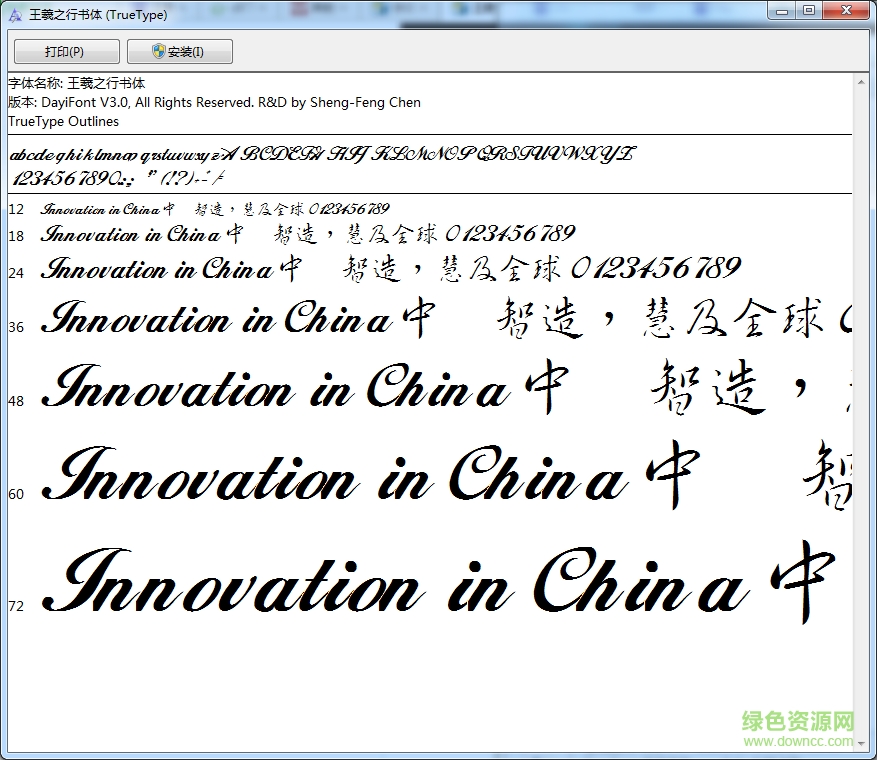
軟件介紹 軟件標簽: 王羲之行書體 字體 王羲之行書體是一款應用領域非常廣泛的書法字體,字體纖細大方,涉及多種行業(yè)使用,可直接導入ps和多種設計軟件中使用。快來綠色資源網(wǎng)下載體驗吧!王羲之行書體介紹本款王羲之字體是王羲之行書字體,下載解壓后將字體復制到C:\WINDOWS\Fonts即可。王羲之出身于一個書法世家的門庭他的伯父王翼,王導;堂兄弟王恬,王洽等都是當時的書法名手。王羲之行書字體安裝方法一:控制面板/字體/文件/安裝新字體;方法二:直接將字體復制到C:\WINDOWS\Fonts。方法三:針對win7系統(tǒng),用戶只需選中字體右鍵安裝即可。 軟件截圖 上一張下一張(1 / 1) 安裝詳細截圖 猜你喜歡 行書字體 行書字體 行書字體包括了鋼筆字行書字體大全、硬筆行書字體等,是一種介于楷書和草書之間的字體。為什么這樣說?因為行書字體既有草書的流暢感,又有楷書的端正感,可以說,行書結合了草書和楷書的特點,形成了獨特好看的行書字體。喜歡的朋友,趕快下載體驗吧! 查看更多>> 繁體行書字體 9.76M/中文/4.0/免費版下載 winman tun10011字體 17.57M/中文/6.6/下載 南構嘉飛行書字體 10.00M/中文/6.6/下載 c g流麗行書體繁/簡 4.39M/中文/5.0/下載 北方行書簡體 2.63M/中文/7.2/下載 qxyingbixing 1.26M/中文/8.0/下載 其他版本下載 標題 大小 更新日期 下載 下載地址 電腦版 王羲之行書體 點擊報錯 軟件無法下載或下載后無法使用,請點擊報錯,謝謝! 關閉報錯反饋 請描述您所遇到的錯誤,我們將盡快予以修正,謝謝! *必填項,請輸入內(nèi)容 本類最新 dreamweaver字體庫 首爾南山體字體 v1.06 官方版 潮字社風云簡ttf 潮字社凌渡鯤鵬簡體字體 潮字社曾玉波手書簡字體 微博慧心字體 相關文章 Photoshop字體安裝使用方法和技巧 如何解決“無法新增字體”問題 Win 7系統(tǒng)安裝字體方法 網(wǎng)頁字體大小設置方法 怎么改網(wǎng)頁字體大小 在Linux系統(tǒng)中安裝字體的幾種方法 windows7字體顯示問題:打開某些程序的時候顯示的是亂碼 用戶評論 熱門評論 最新評論 發(fā)表評論 查看所有評論(0) 昵稱: 請不要評論無意義或臟話,我們所有評論會有人工審核. 字數(shù): 0/500 (您的評論需要經(jīng)過審核才能顯示)